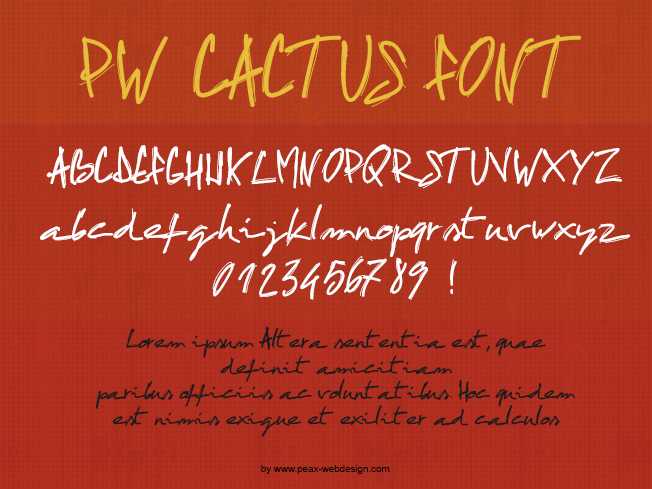
La police PW Cactus est dans un style un peu BD, et dédoublée sur les bords. Elle est très dynamique, et comprend les cacactères majuscules, minuscules et les chiffres.
Utilisation conseillée : grande taille, bien qu'également lisible en petite taille. Elle est gratuite pour un usage personnel uniquement. Pour une utilisation commerciale, me contacter.